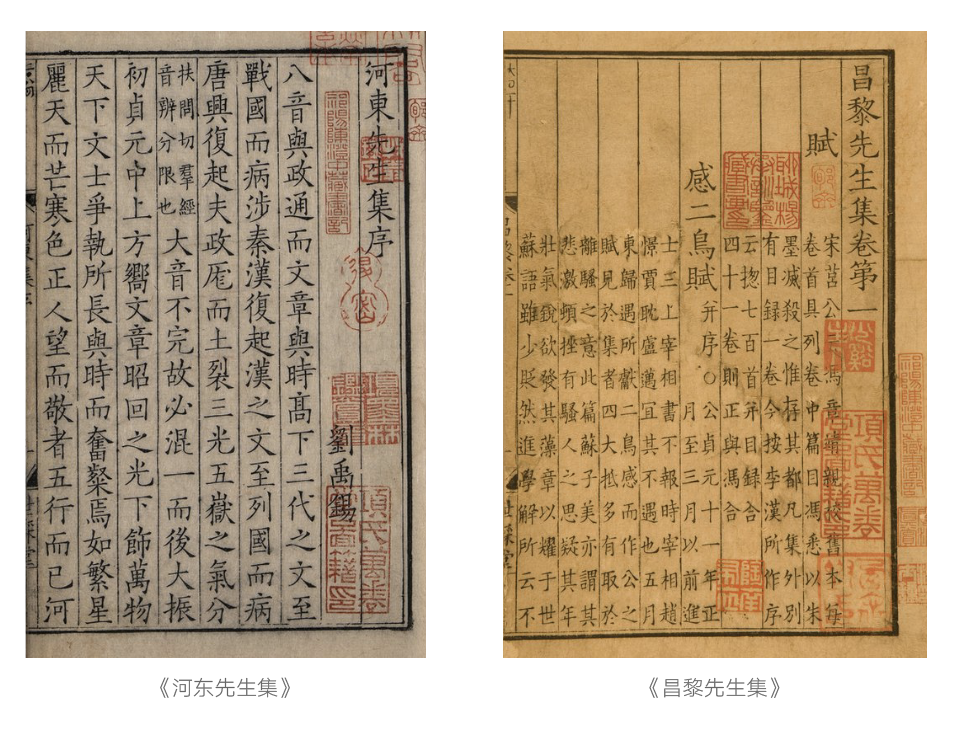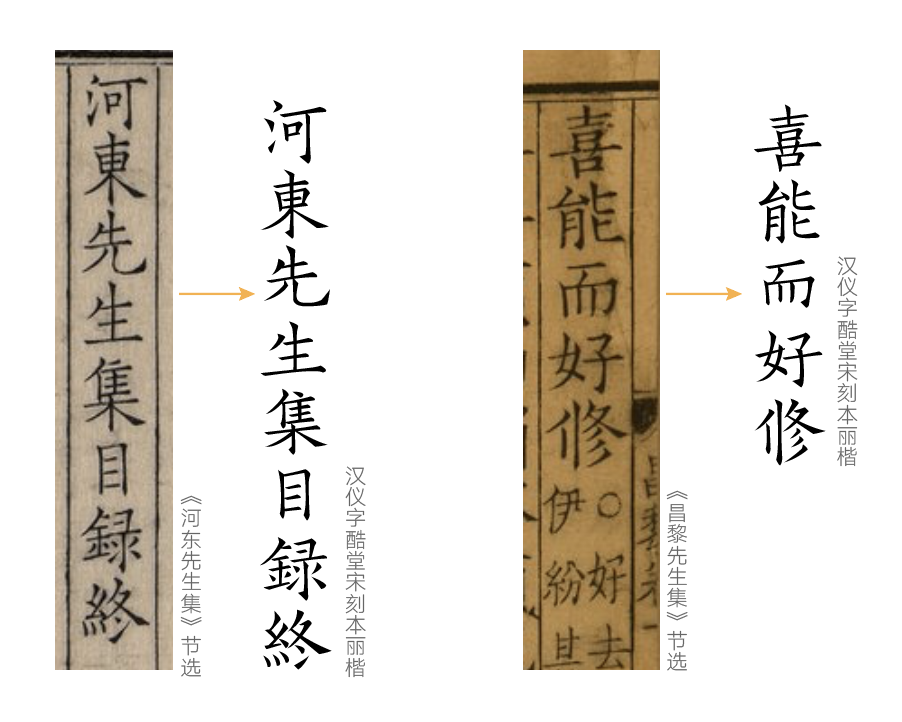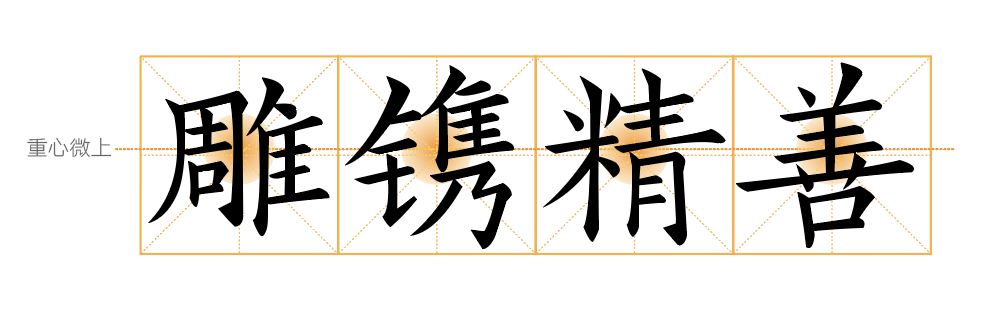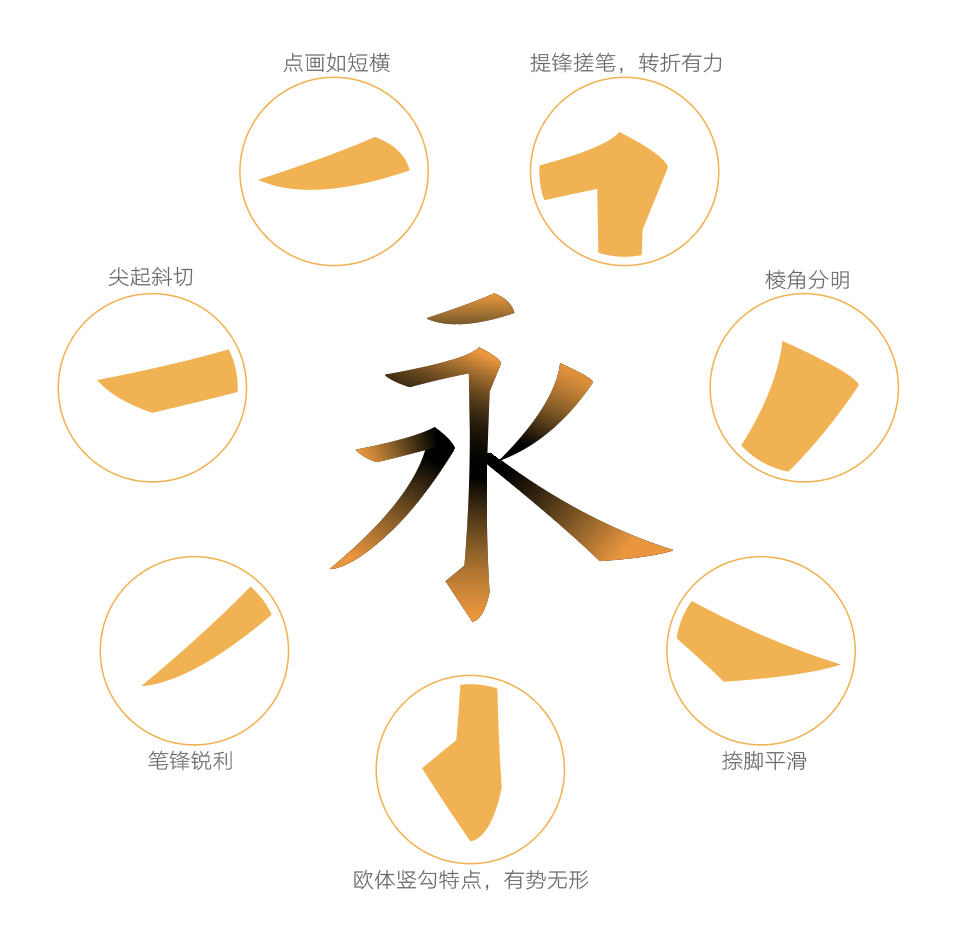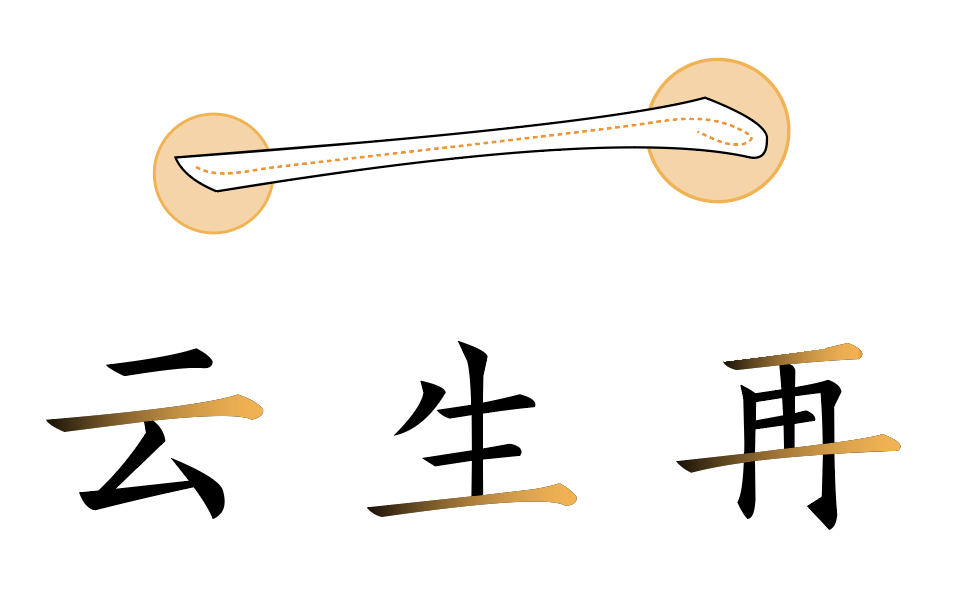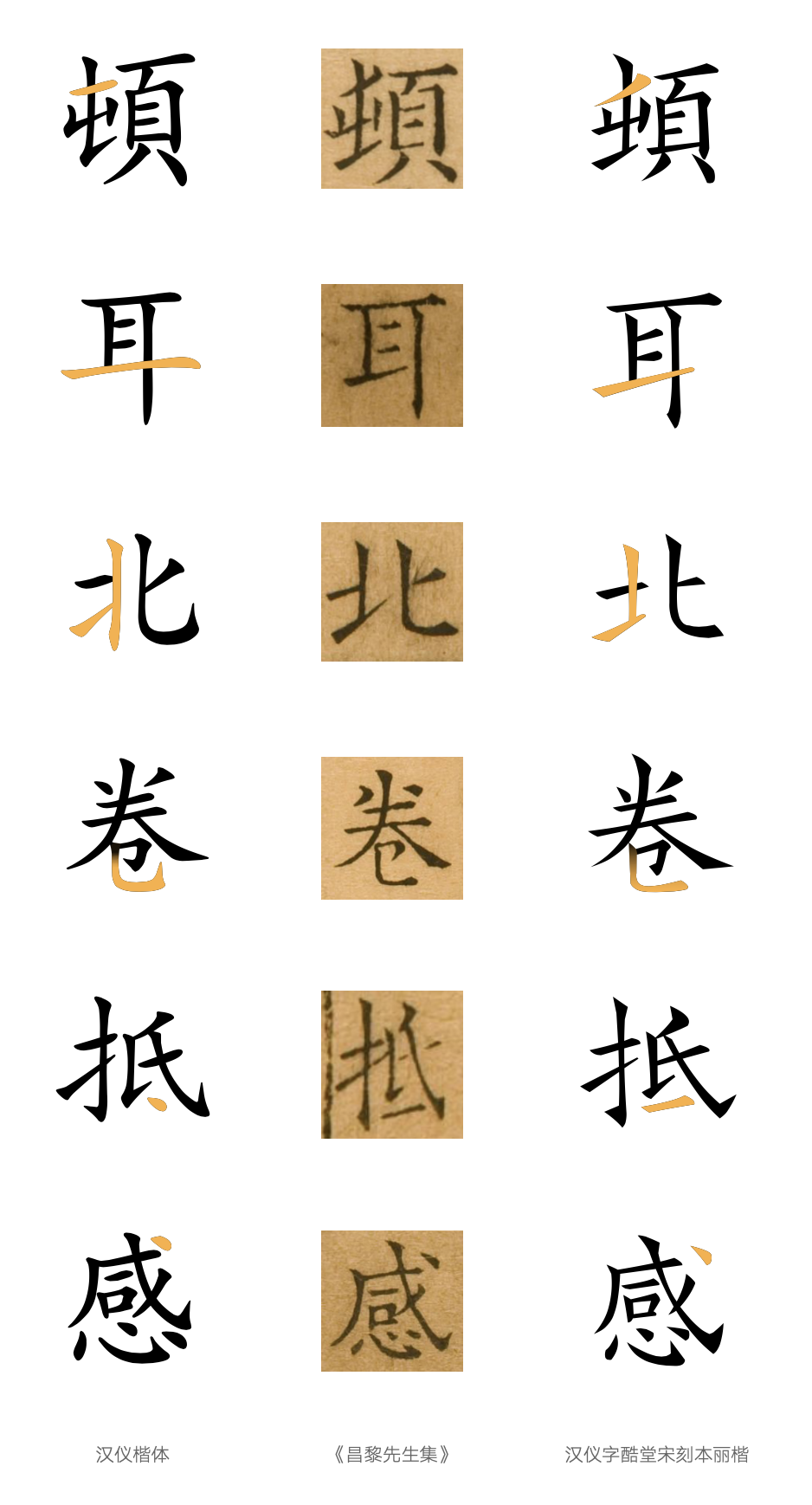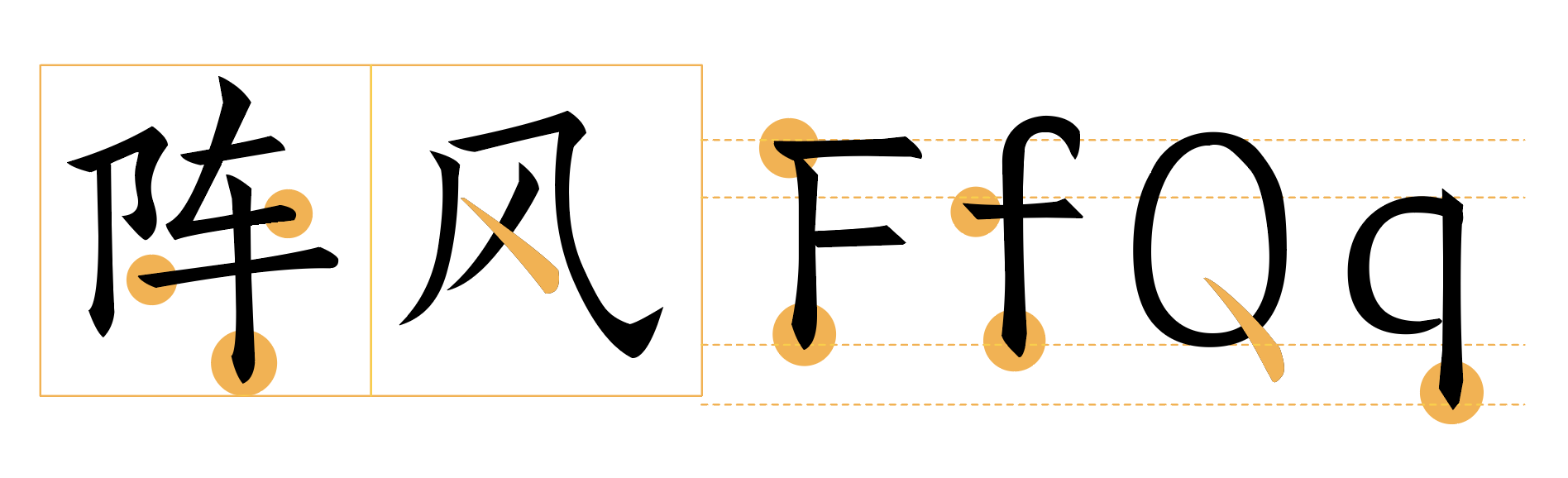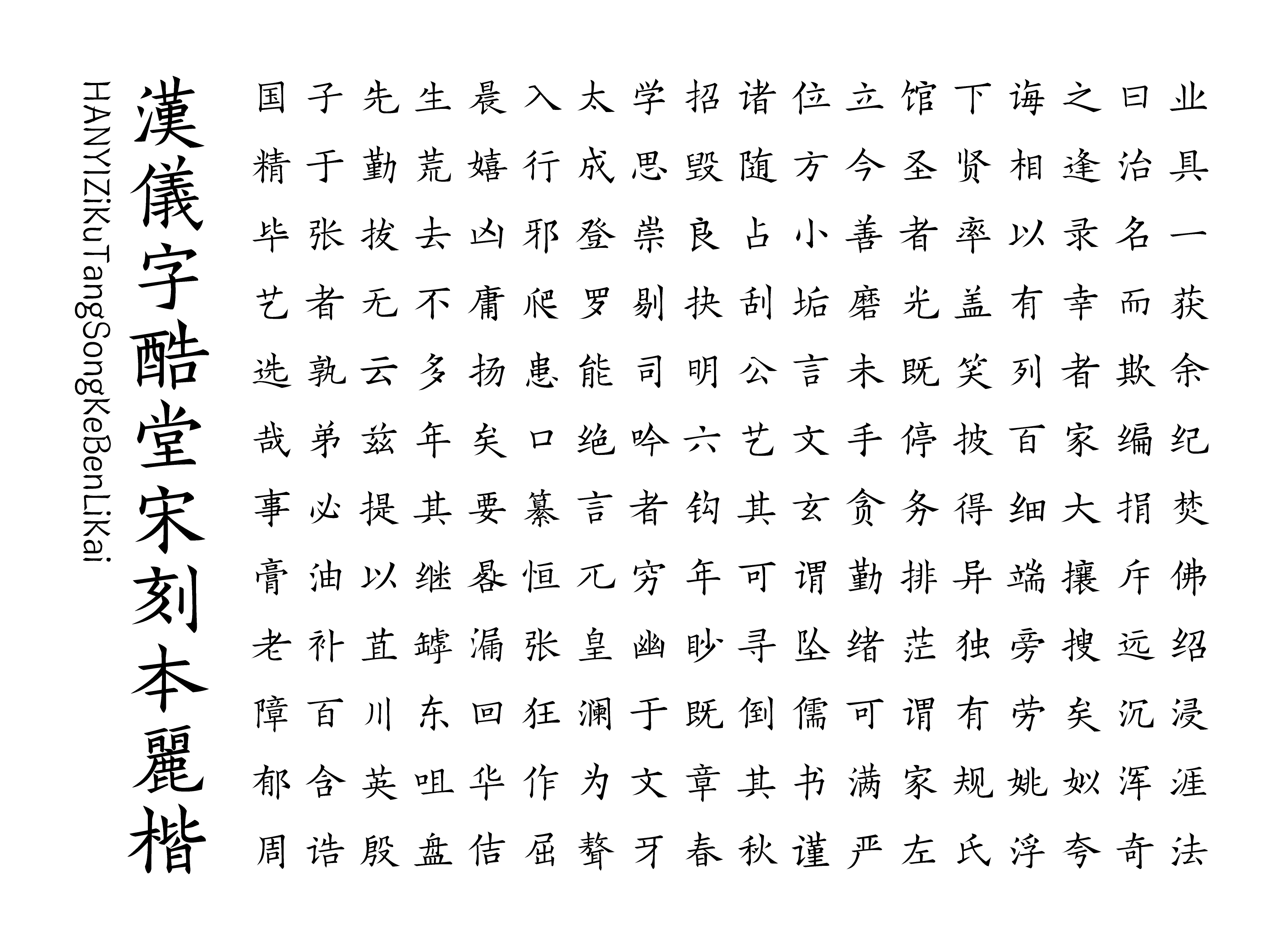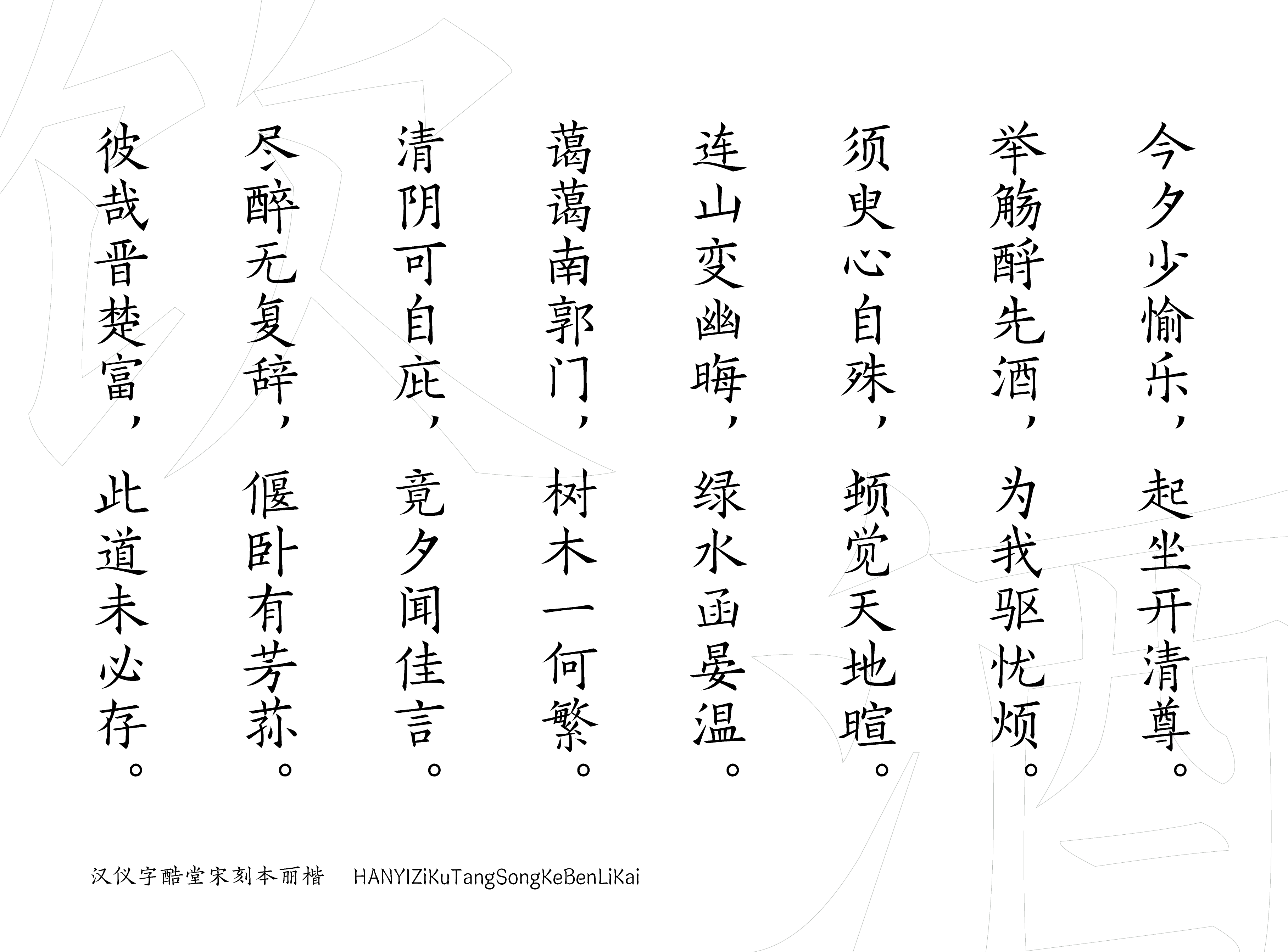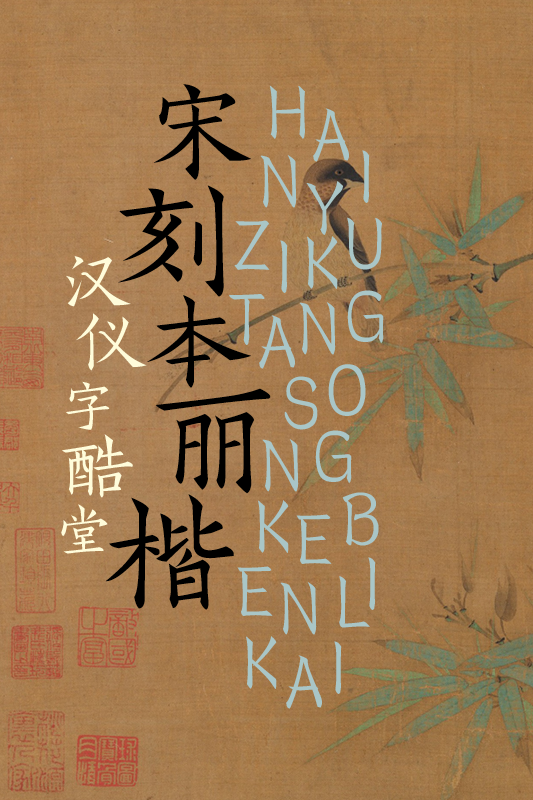
汉仪字酷堂宋刻本丽楷字体介绍
楷书/复刻
中国风 / 古典 / 秀逸 / 挺拔 / 劲道
字体来源
汉仪字酷堂宋刻本丽楷是汉仪旗下“字酷堂”工作室设计的一款刻本字体。这款字以宋刻本《河东先生集》和《昌黎先生集》为蓝本,二集同时由廖氏世綵堂刊版,皆刀法剔透,写刻精美,摹刻逼近原刻,世称善本,被誉为宋版书中的“无上神品”。
汉仪字酷堂宋刻本丽楷作为一款复刻字体,保持了原刻本字形规整、笔画坚挺、骨气内含的风格特点,在贴近书法原貌的同时,也注重字符的易读性和辨识度。可用于古文、诗歌、短文的排版以及文化类的品牌设计。
字形瘦劲挺拔
汉仪字酷堂宋刻本丽楷瘦劲挺拔,极具骨力;结构中宫紧凑,向外拓展;布白上较为宽绰。
笔画劲中含润
汉仪字酷堂宋刻本用笔以出锋为主,方折瘦劲,同时又内含秀骨,笔势舒张,不失润味。
汉仪字酷堂宋刻本用笔方圆兼施,以方为主。横画左低右高,露锋入笔,笔锋尖锐,然后很缓的过渡,收笔内敛,形成成一个圆弧头。
贴近书法原貌,还原刻本
汉仪字酷堂宋刻本丽楷贴近书法原貌,遵从了传统的书写方式,使其在布白均衡且易识别的前提下,还原了刻本古拙的味道。
中西文匹配
汉仪字酷堂宋刻本丽楷的西文在笔画上加入了一些书写特点,以呼应中文的特性,在与中文搭配使用时十分和谐。
排版效果
海报样张